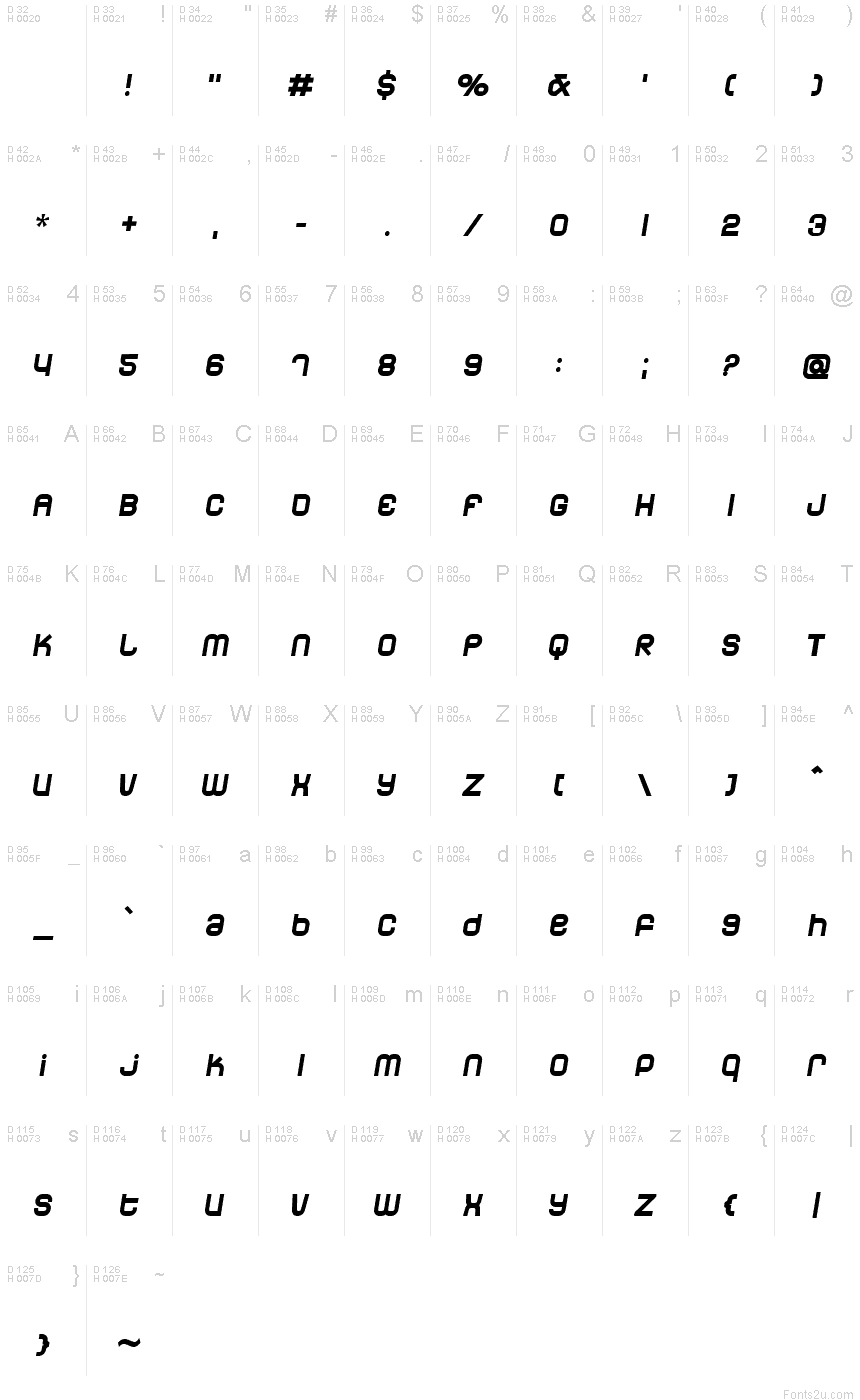
Dunebug 45MPH
Dunebug 45MPH od Fontalicious Fonts to nowoczesny, darmowy krój typu display, który przypomina numery malowane na rowerach wyścigowych. Jego masywne, zaokrąglone pociągnięcia są nachylone do przodu, dzięki czemu każde słowo zdaje się pędzić naprzód. Litery są ciasno osadzone, a miękkie, owalne kształty nadają im szybką, przyjazną energię, unikając przy tym agresywnego charakteru.
Ten darmowy font świetnie sprawdza się w brandingu sportowym, na plakatach wyścigowych, grafikach motoryzacyjnych, w tytułach gier, nakładkach streamingowych czy efektownych bannerach w mediach społecznościowych, gdzie liczy się dynamika nawet w statycznej ramie. Użyj Dunebug 45MPH w dużych nagłówkach z odpowiednim odstępem między literami, aby pozwolić tym pochyłym formom oddychać i zachować czytelność. Zestaw go z prostym, neutralnym krojem bezszeryfowym w tekście głównym, aby skierować wzrok na odważny, szybki rytm logo lub tytułu.